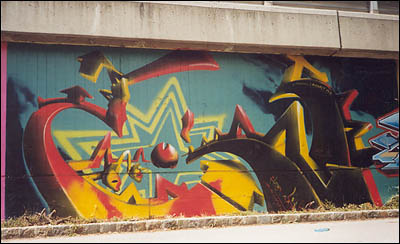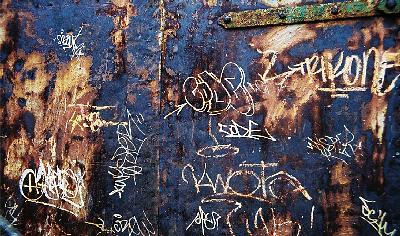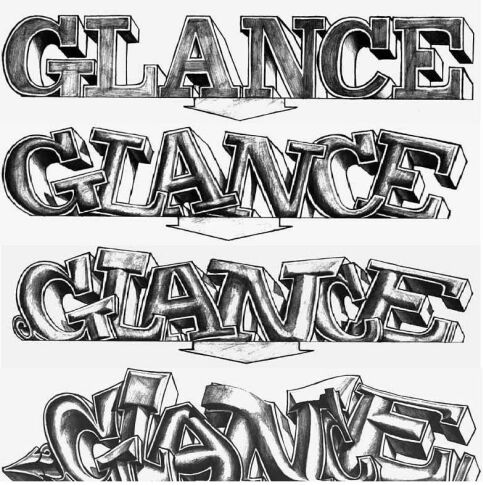
Wo seht ihr Unterschiede, wo Gemeinsamkeiten zwischen der traditionellen Typographie - inklusive heutiger Display-Schriften - und Graffiti? Habt ihr euch überhaupt mit dieser Kultur auseinandergesetzt?
Ich war nie Sprayer, jedoch seit längerer Zeit interessiert. Über das Bild oben stolperte ich vor einigen Wochen. Ehrlich gesagt gefällt mir die oberste Linie am besten…
Ich kenne genau zwei Sprayer beim Namen: Daim und und Loomit.
Zusätzlich gibt es ja noch die "Kunst" der Tags, bei dem Leute ihre Namen mehr oder weniger kunstvoll verzieren.